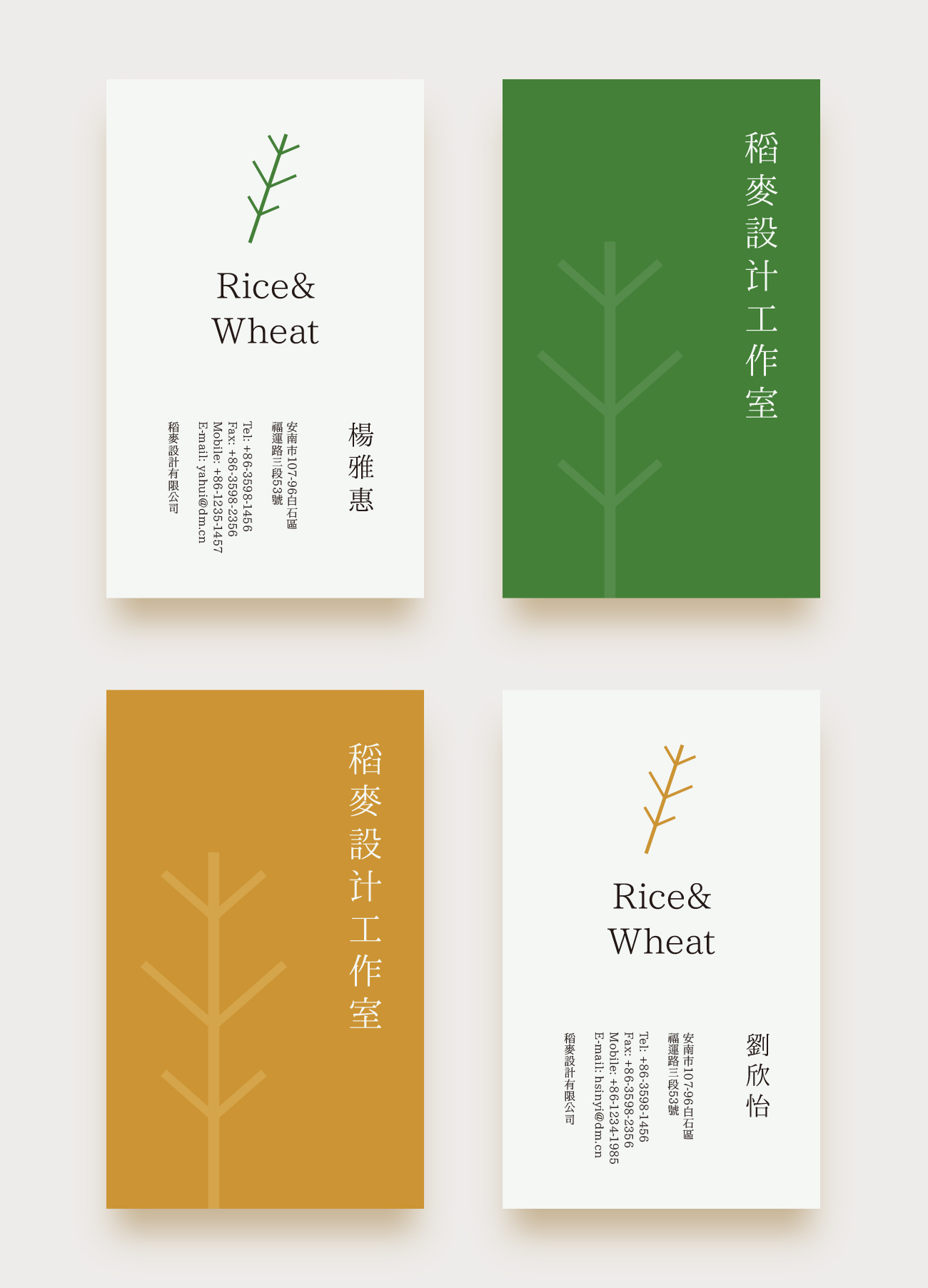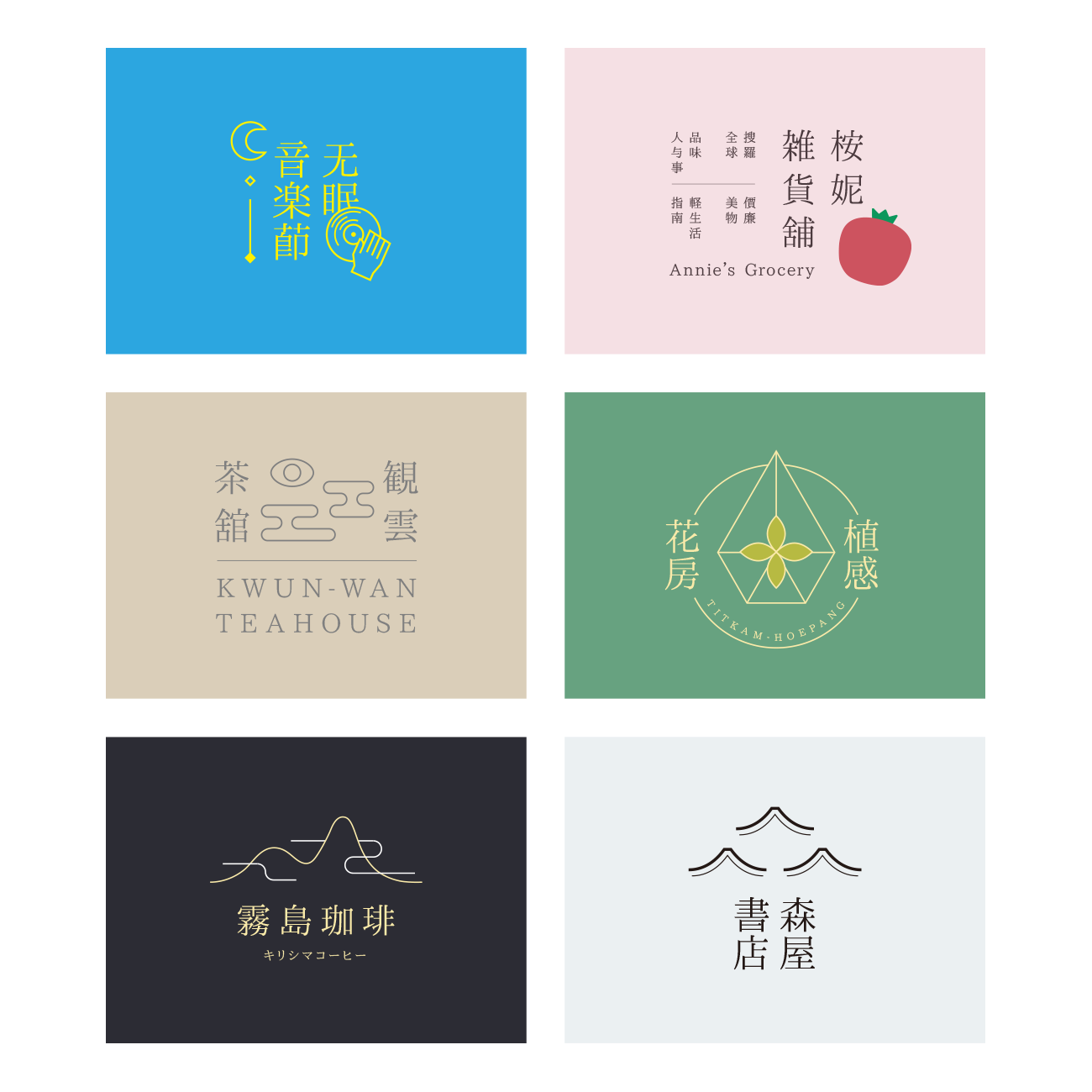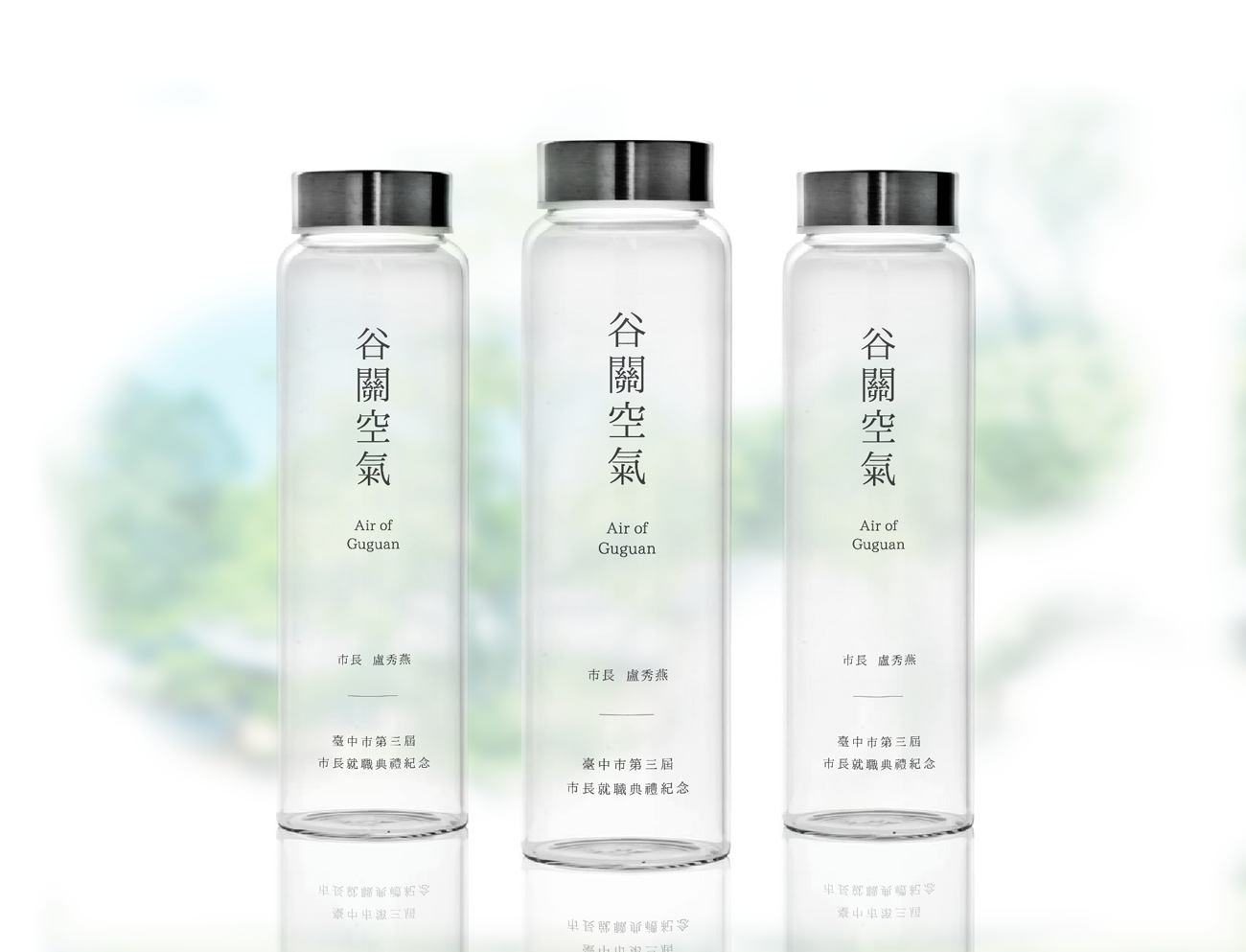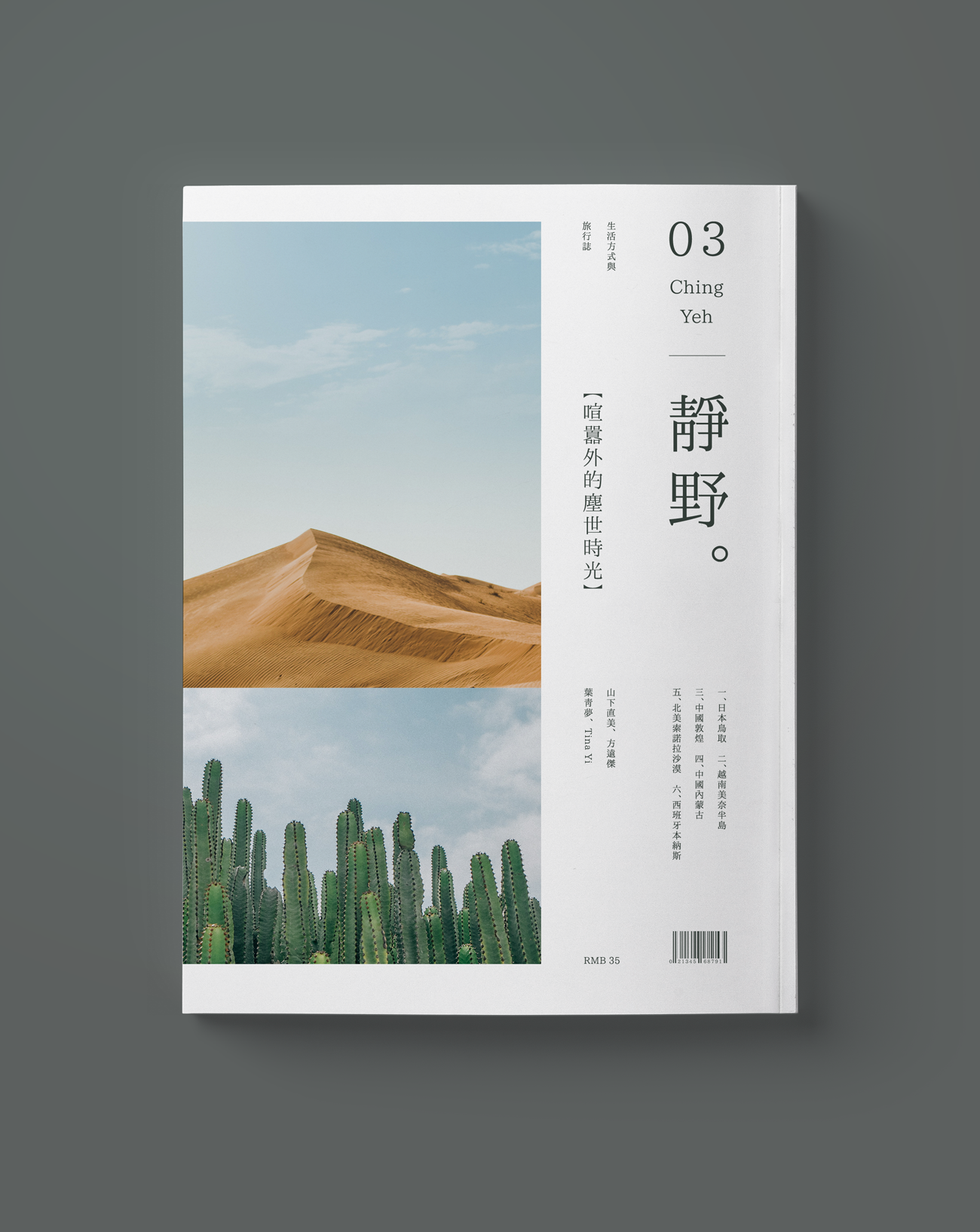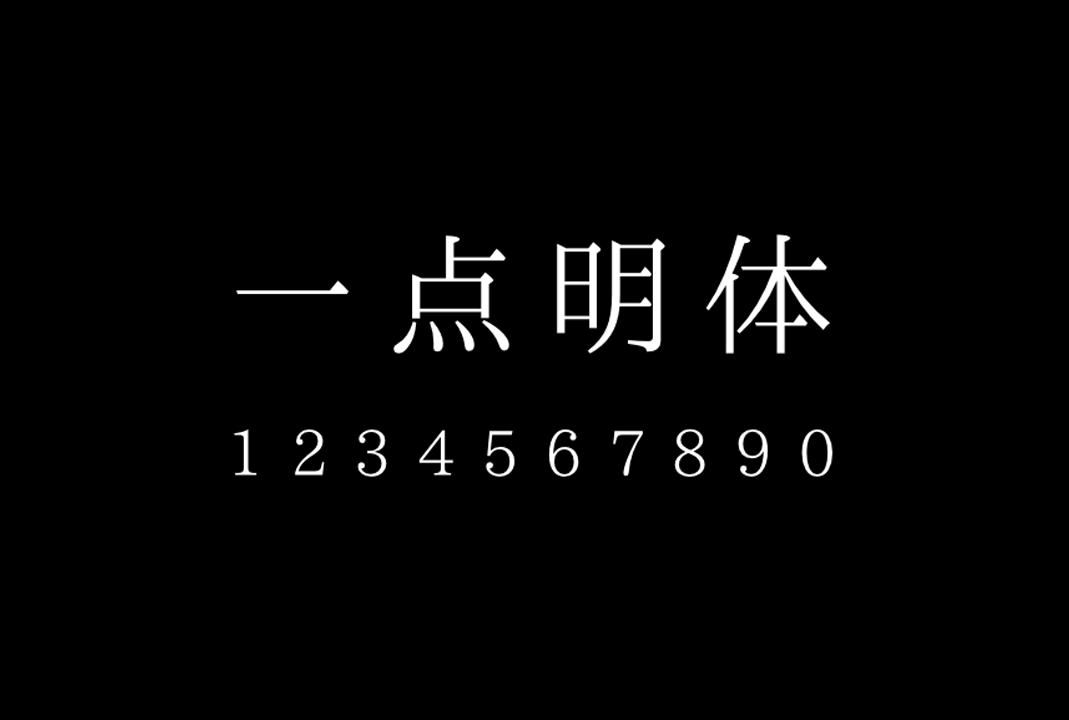
一点明体的前身是刻石录明体,已由开源字型组织I.字坊(一点字坊)全力维护。明朝体在我们中国其实就是宋体,只是日本、韩国等国家才称为明体或明朝体。该字体已于2020年09月17日更新7.00版本,除了原来的正体(繁体)、日韩汉字、粤台闽客汉字等传承字形,以及注音符号、麻雀版、苏州码子,象棋等,也制作了旧字形的简化字,不会再碰到繁简不分的问题。
「I.明体」(I.Ming):收录力求遵从字理的传承字形。
「I.明体CP」(I.MingCP):与「I.明体」一样,唯全形标点置中。
「I.明体异体」(I.MingVar):部份汉字改爲收录一些也常见,但字理上未必比上者佔优的传承字形。
「I.明体异体CP」(I.MingVarCP):与「I.明体异体」一样,唯全形标点置中。